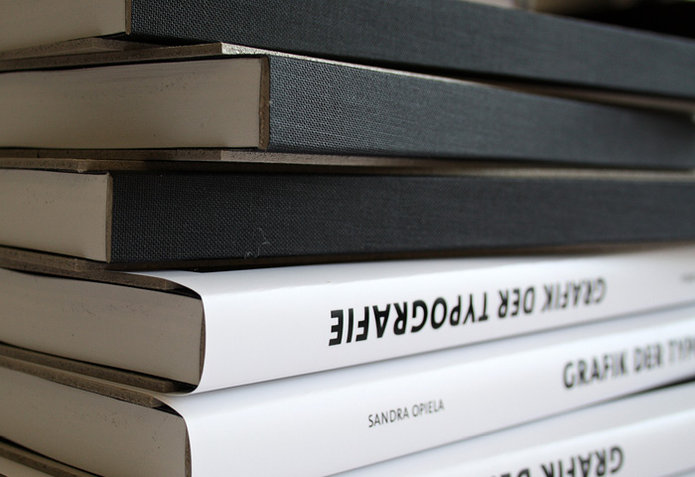
Masterthesis. Didaktisches Konzept zur Vermittlung typografischer Grundlagen.
Welche unsichtbaren und nie beachteten grafischen Formen und Besonderheiten verstecken sich in der Typografie? Wie kann man die Vielfalt entdecken, sichtbar machen und nutzen? Anhand ausgewählter Beispiele zeigt das didaktische Konzept "Grafik der Typografie" verschiedenste Gestaltungsprozesse, die versteckte Details der Typografie offenbaren. Die Typografie und ihre dahinterliegenden Denkmuster werden benutzt, um Unsichtbares sichtbar zu machen, Grundlagen zur typografischen Gestaltung zu vermitteln und Besonderheiten zu entdecken. Entdecktes wird grafisch übersetzt und präsentiert. Die Typografie wird zur Grafik. Man soll sich davon lösen die Grundlagen durchzuexerzieren und feste Abläufe einhalten zu müssen. Stattdessen sind Experimente erlaubt, die es ermöglichen, die typografischen Grundlagen selbstständig zu untersuchen und zu erarbeiten. Die Grundlagen der typografischen Gestaltung werden zu einer vielseitigen und experimentellen Herausforderung mit unerwarteten Ergebnissen.
Broschur, 202 Seiten Inhalt. 25 x 32 cm, Buchblock aus 2 mm Graupappe mit Schutzumschlag. www.sandraopiela.de